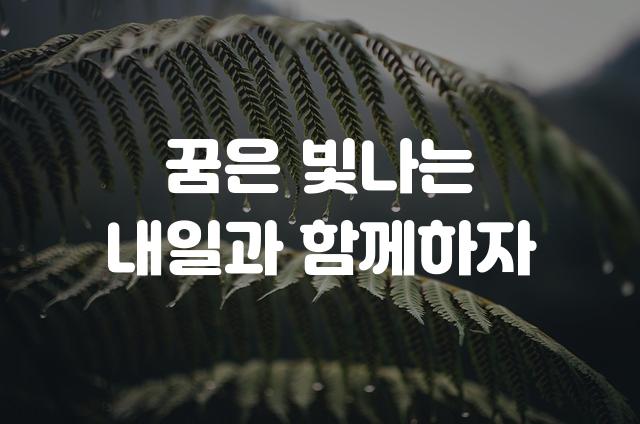
‘여기어때 잘난체 고딕’은 기본 고딕 스타일에 두꺼운 특징을 결합한 제목용 폰트입니다. 강렬하고 선명한 라인이 특징적이며, 모던하면서도 강한 인상을 줍니다.
여기어때 잘난체 고딕은(는)
기본 고딕, 두꺼운 스타일, 굵은 고딕, 감성적인, 단단함, 부드러움, 길고/크고 계열의 생김새를 가지고 있으며
디지털 광고, 카페 메뉴, 소셜 미디어 등에서 자주 활용되며, 효과적인 메시지 전달에 적합합니다.
이 폰트는 음식/식음료, 라이프스타일, 소매/유통 분야에 잘 어울리며,
친근한, 귀여운, 재미있는 느낌을 담고 있는 것이 특징입니다.